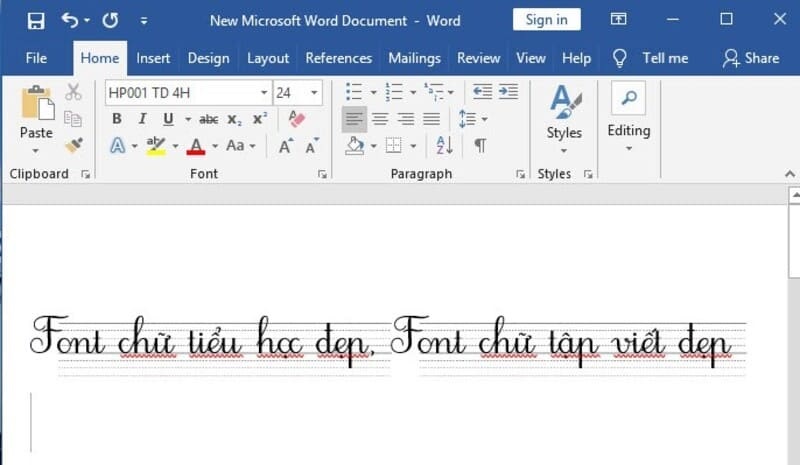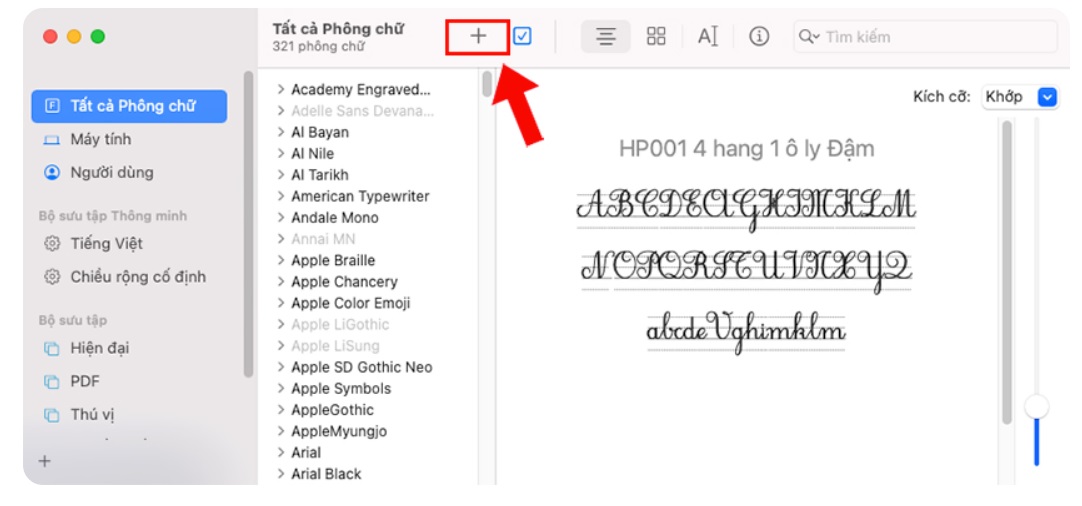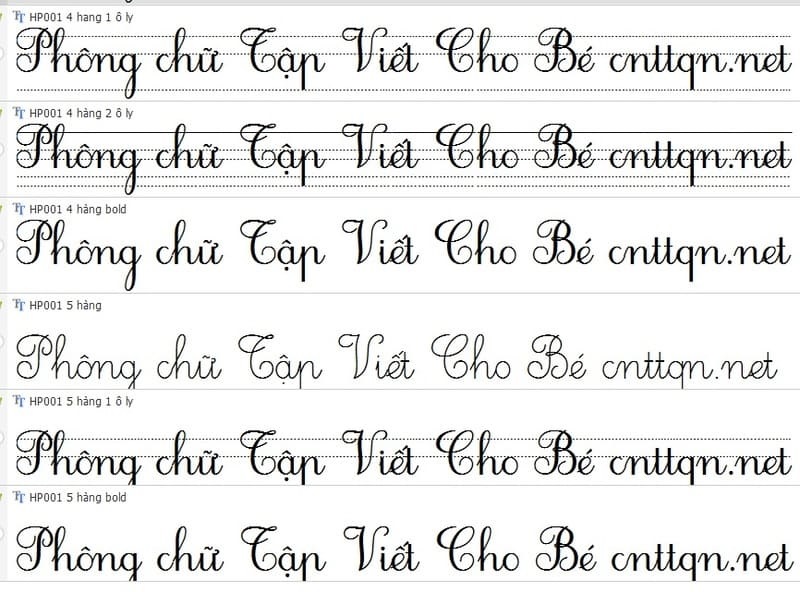
Các font chữ dành cho học sinh tiểu học là công cụ giúp trẻ bước đầu làm quen với mặt chữ, nâng cao khả năng đọc và viết. Những kiểu chữ này có thiết kế tối giản, dễ nhìn, phù hợp để trẻ quan sát và luyện viết theo. Bài viết sau sẽ hướng dẫn chi tiết về cách cài Font chữ tiểu học cho Macbook siêu đẹp. Cùng theo dõi ngay nhé.
Font chữ tiểu học là bộ kiểu chữ tiếng Việt được thiết kế chuyên biệt cho học sinh cấp một. Bộ font này bao gồm đầy đủ bảng chữ cái tiếng Việt, từ chữ in hoa đến chữ thường, mô phỏng đúng định dạng chữ trong sách giáo khoa và vở tập viết, giúp các em dễ dàng tiếp cận và luyện tập chữ viết tay theo chuẩn chữ viết học đường.
Những font chữ tập viết này được phát triển dựa trên các quy định của Bộ Giáo dục và Đào tạo, giúp giáo viên dễ dàng tích hợp vào các tiết học trên lớp.
Bên cạnh đó, phụ huynh cũng có thể sử dụng để hỗ trợ con em luyện viết tại nhà bài bản. Đây là một công cụ hữu hiệu, góp phần vào việc hình thành kỹ năng viết đúng chuẩn ngay từ những năm đầu đi học.